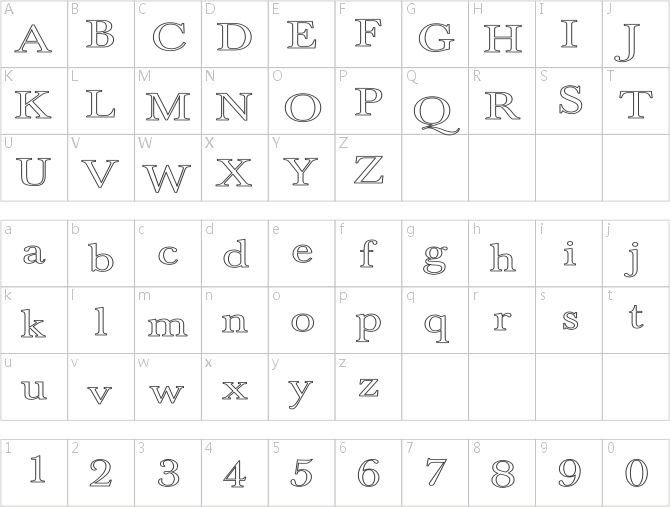
NewBaskerville-Normal-HW
NewBaskerville-Normal-HW介绍
NewBaskerville-Normal-HW字体字库是一款让人赏心悦目、百看不厌的英文字体,适合各类广告和产品包装设计应用,字体大小0.19MB,格式为ttf字体,上传用户是KISEKI,作者/版权方为未知